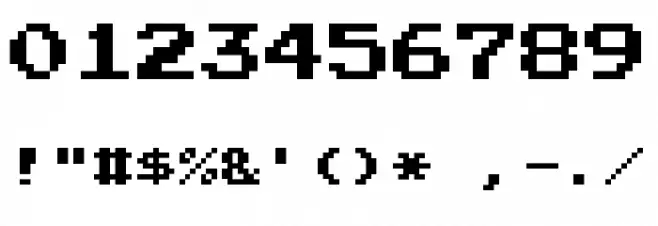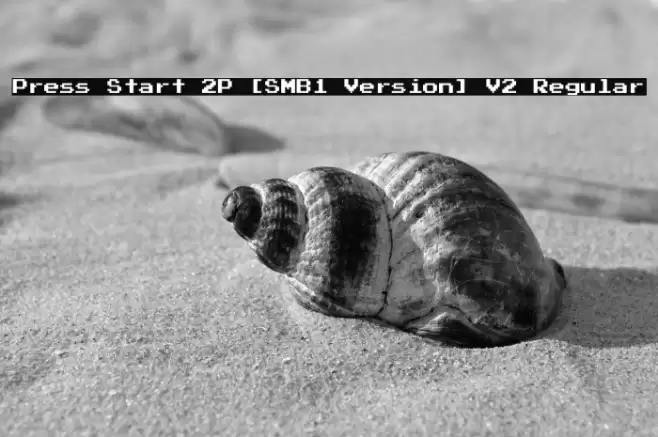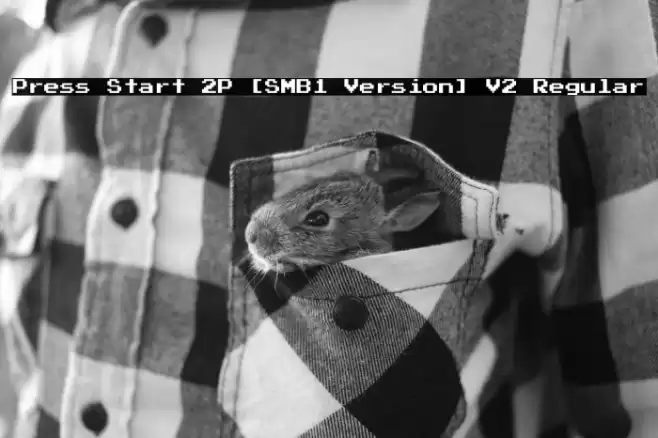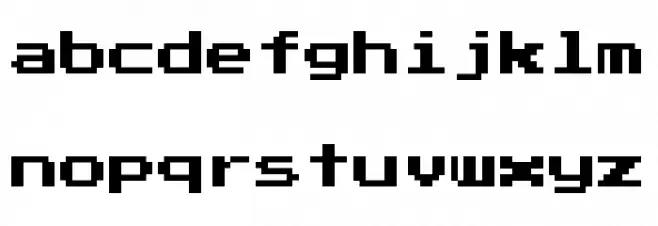
Press Start 2P [SMB1 Version] V2 Regular Font
| Gesamtstil | Vintage |
| Anwendungsfall | Logos, Headlines, Digital Art |
| Vorgeschlagene Projekte | Ideal for video game design, retro-themed posters, digital art, and any project seeking a nostalgic or tech-inspired aesthetic. |